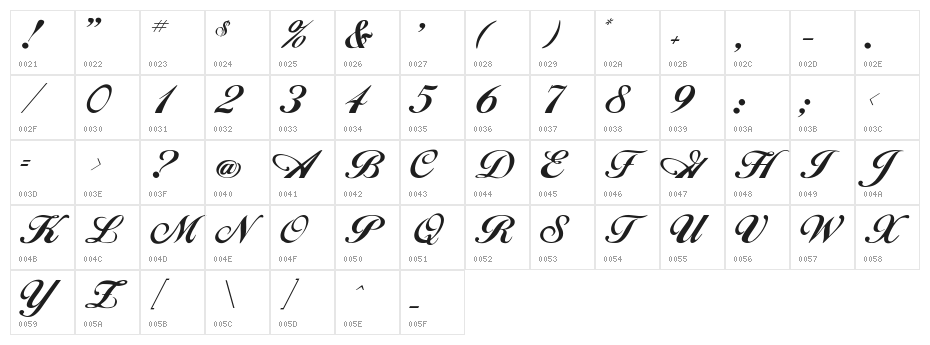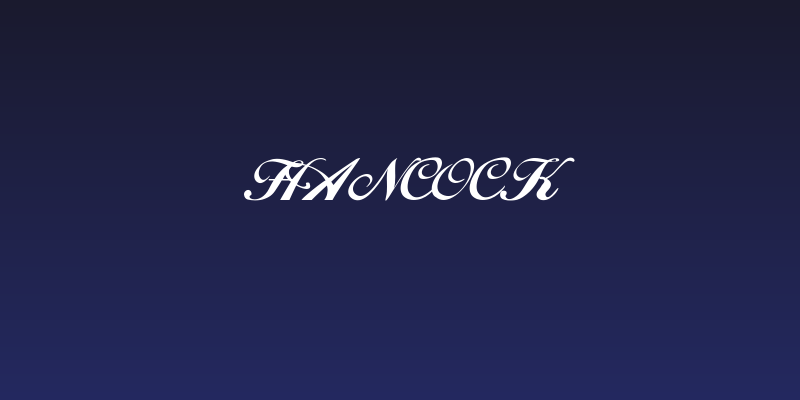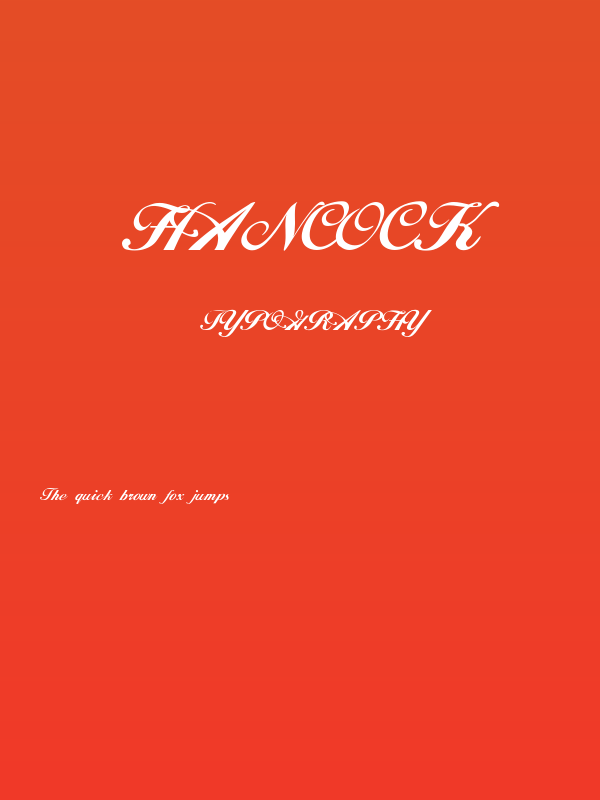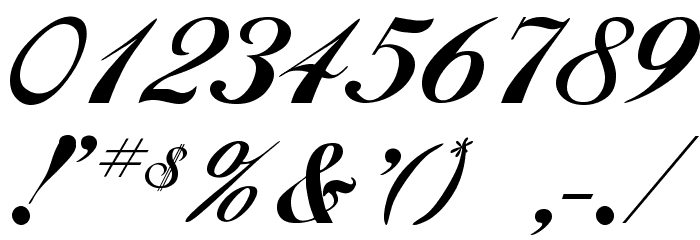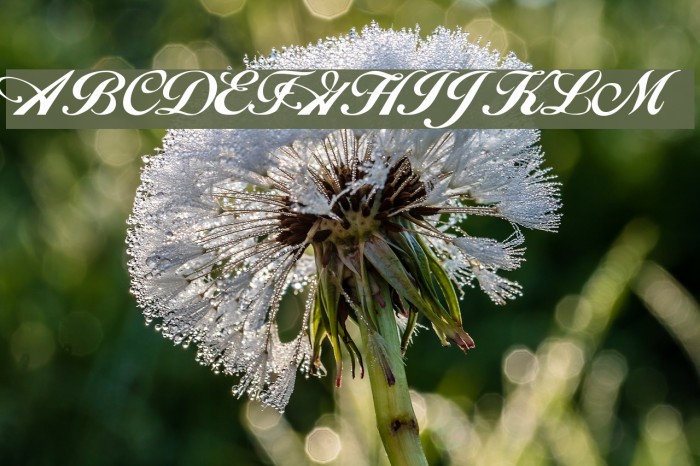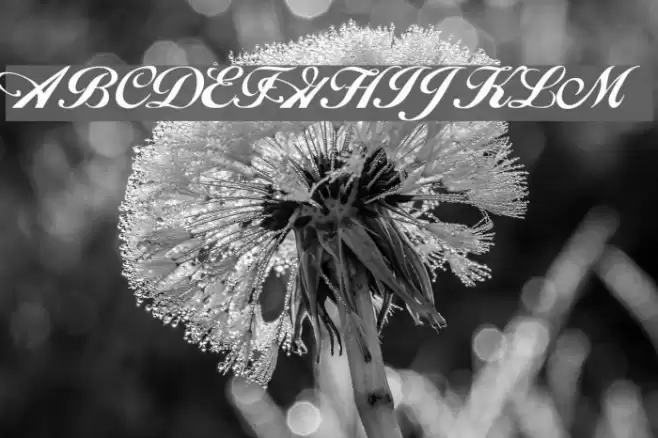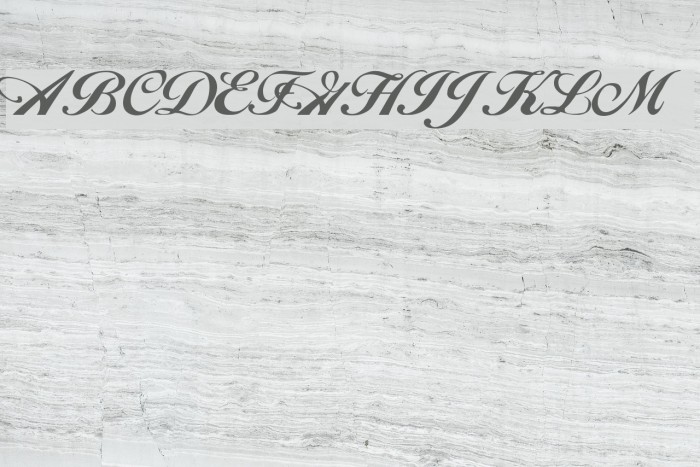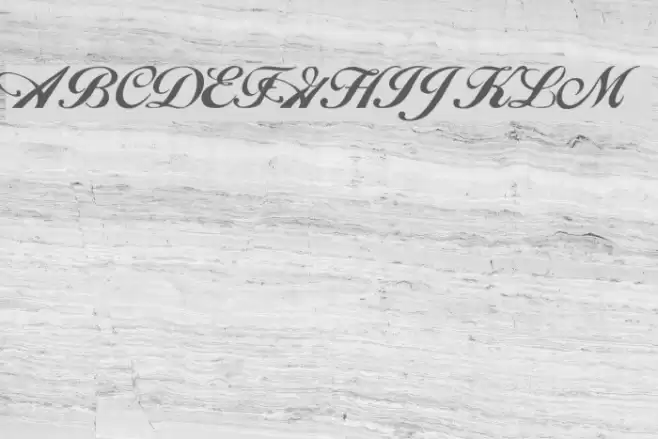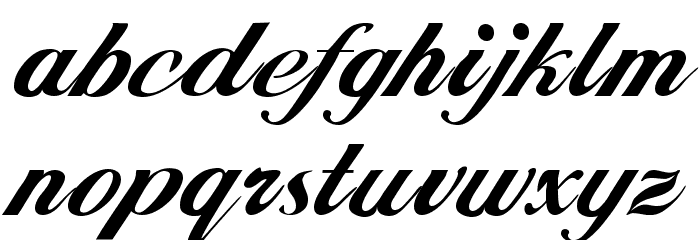
Hancock Font
| Stil general | Elegant, Decorative |
| Caz de utilizare | Headlines, Invitations, Branding |
| Proiecte propuse | Ideal for wedding invitations, luxury branding, elegant signage, and sophisticated editorial design. |